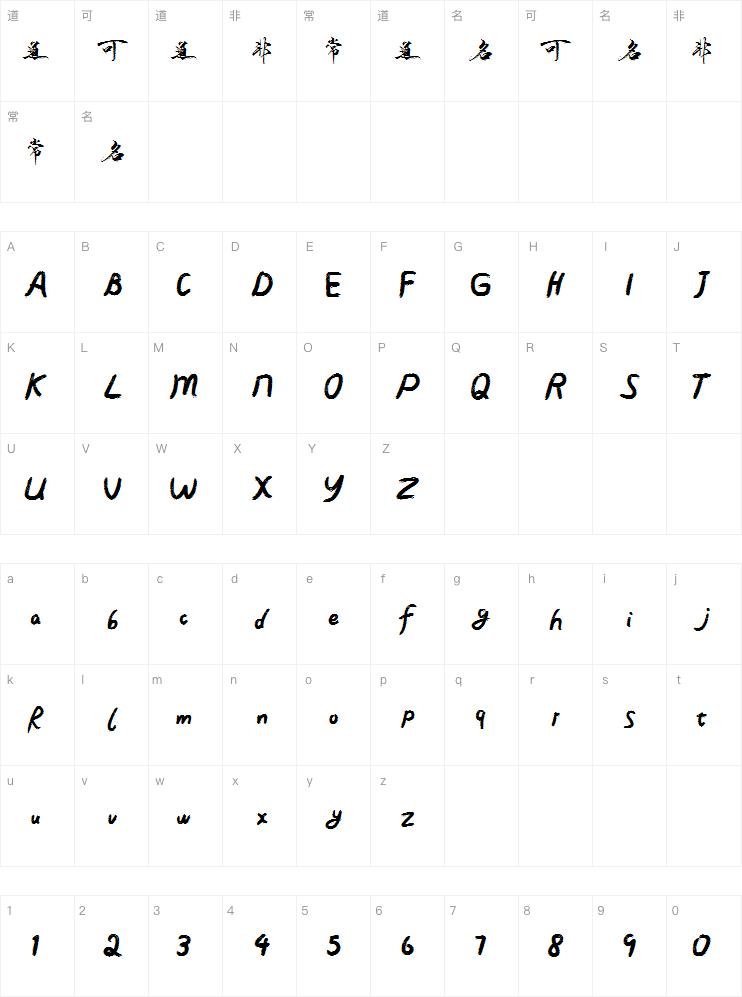
国风木兰行书简体整体呈现出行书的特点,笔画流畅自然,有一定的连笔和呼应,书写感较为灵动。同时,作为简体字,结构规整清晰,便于识别。风格上兼具行书的洒脱与简体字的简洁实用,既保留了行书书写时的韵律与灵动性,又符合现代简体字的使用习惯,适合用于需要体现书写美感且追求清晰易读的场景,如文创设计、标题排版、日常文字创作等。